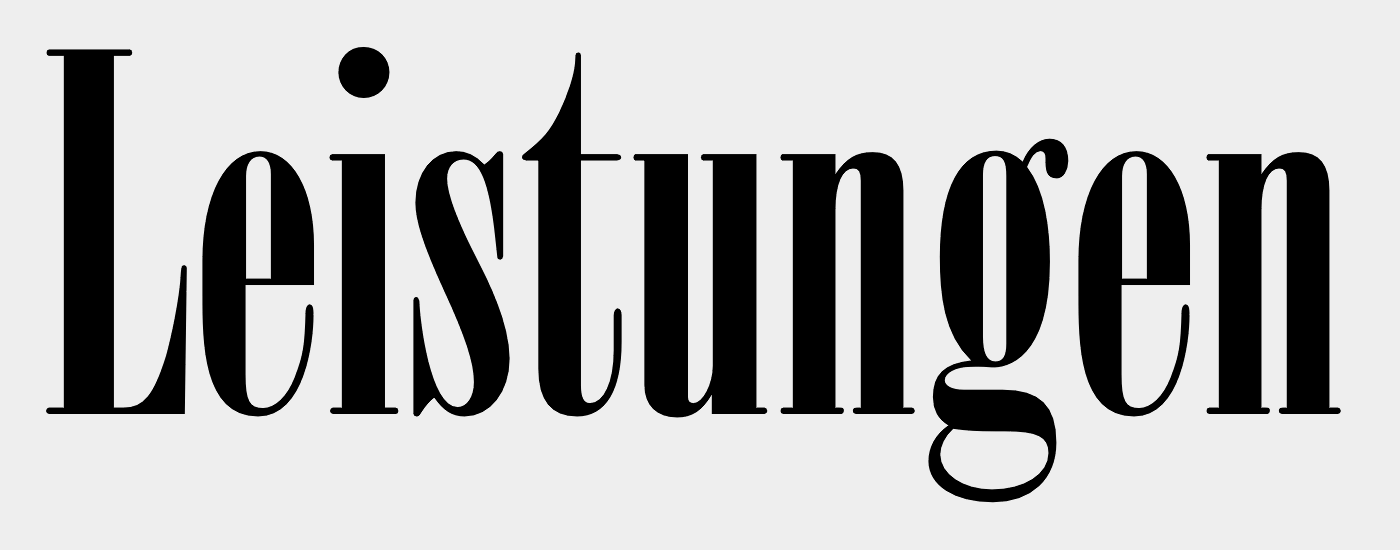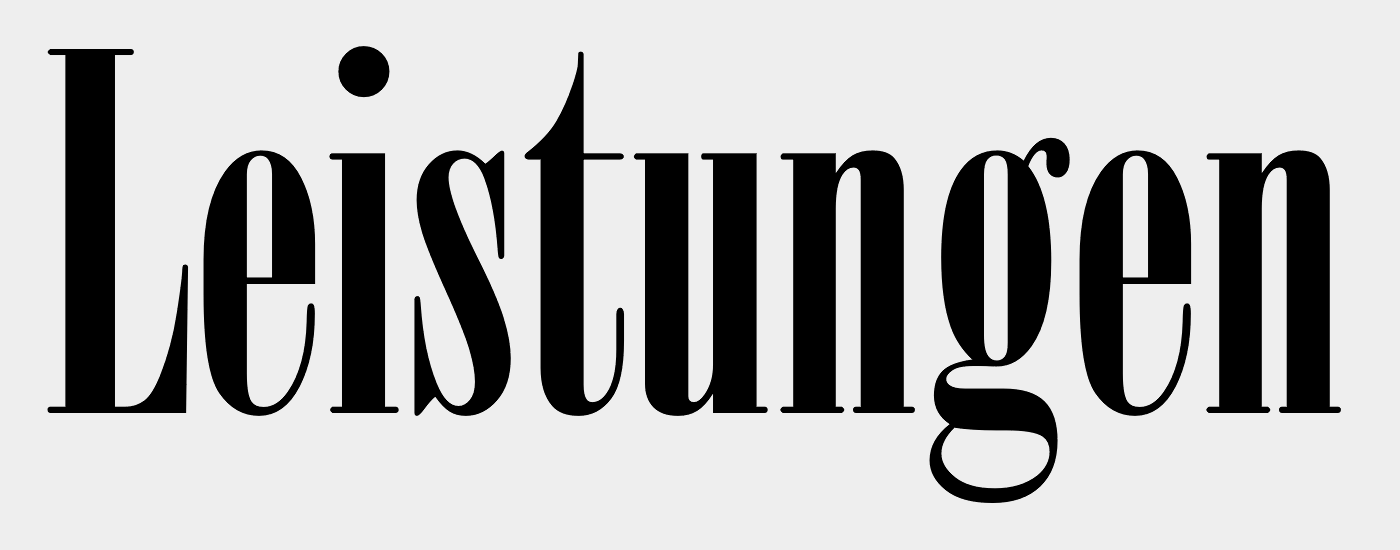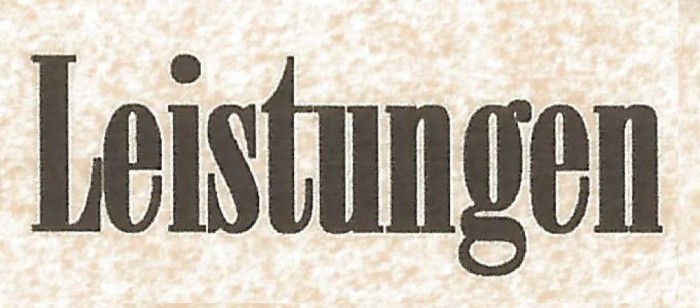
Welche Schrift ist das? (Leistungen)
diese Schrift geht gegen die Onyx ... Aber derer gibt es viele ... Auf ersten Blick erscheint mir die Version von Bitstream am erfolgsversprechenden und man findet sie in den Schriftpaketen die mit Corelprodukten wie Draw ausgeliefert wurden:
Hier mal eine Hilfestellung bei der Suche in den Bitstreamsammlungen:
Die Monotypeversionen sind IMHO eher unpassend:
Es gibt da noch zwei Alternativen: Die OptiOnyx ist sowas wie Abandonware und damit frei erhältlich:
Von K-Type gibt es eine Sardonyx mit leicht aufpolierten Formen:
Ich würde auf eine leicht verfettete Onyx BT tippen und dafür die Hand nicht ins Tiefkühlfach legen wollen.
Und ich hatte noch gedacht: Nee, Onyx kann es nicht sein, weil die nicht so fett ist. Aber vielleicht hat jemand eine Kontur drumgelegt, das würde auch erklären, warum die stellenweise so zuläuft.